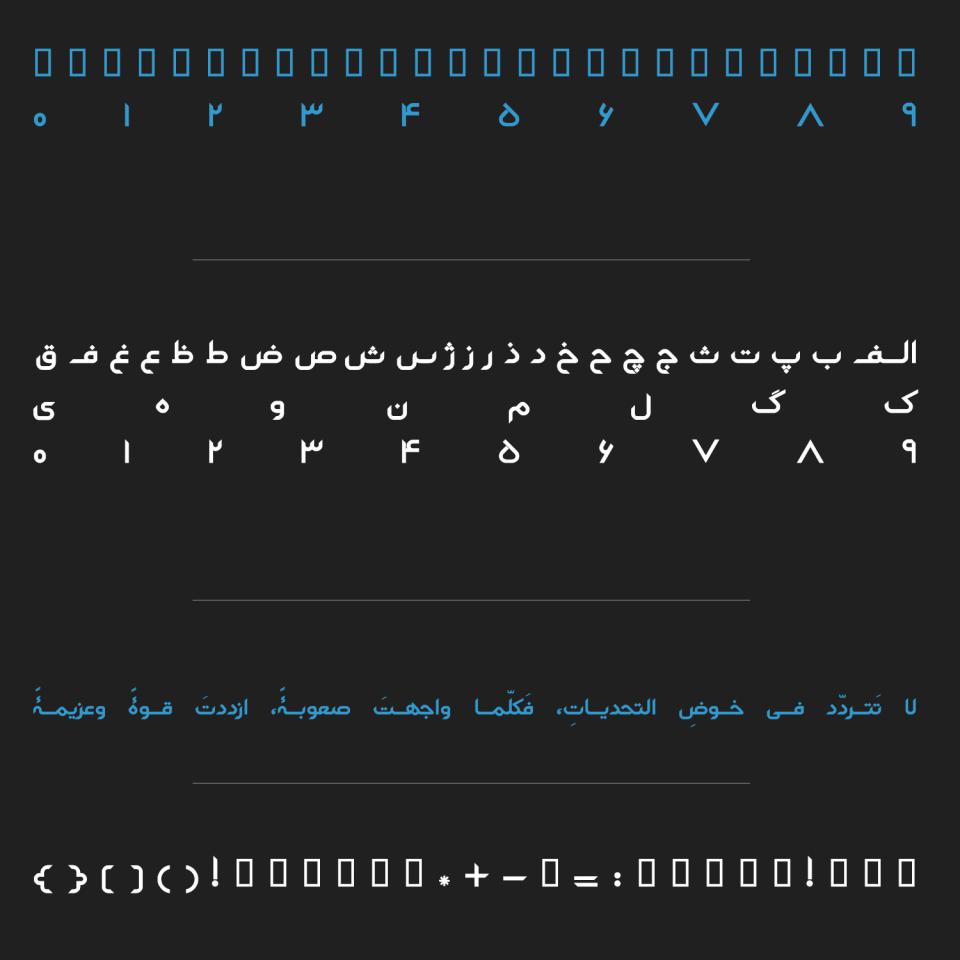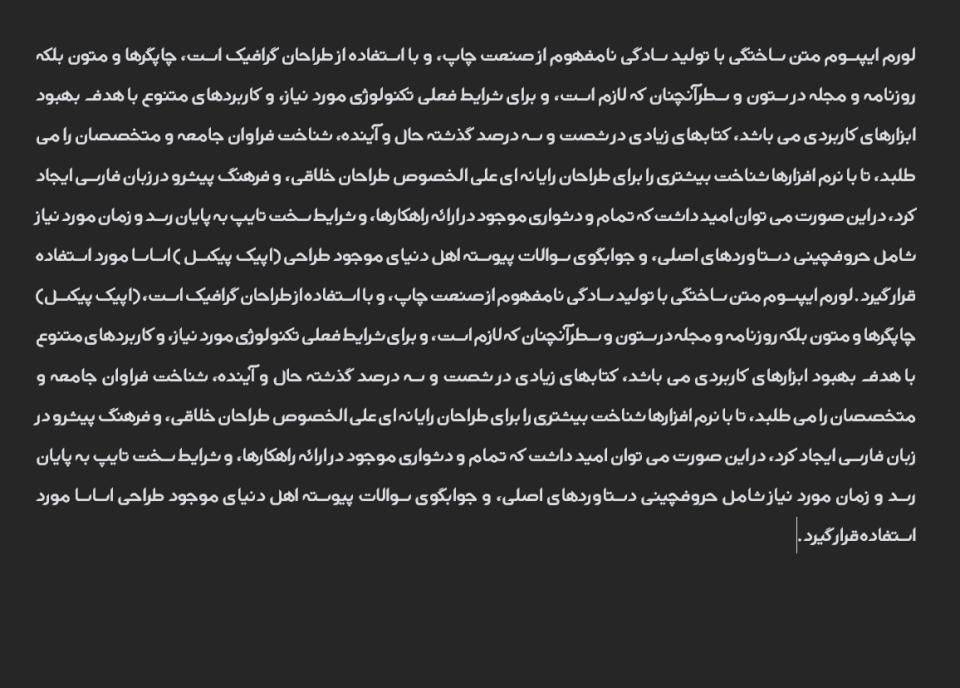
5 فونت آسمان فارسی
یکی از ویژگی های برجسته فونت آسمان، طراحی منحصربه فرد حروف آن است که هم در متن های طولانی و هم در عناوین کوتاه، خوانایی بالایی را ارائه می دهد. این ویژگی، آسمان را به گزینه ای مناسب برای طراحی لوگو، پوستر، وب سایت و سایر پروژه های گرافیکی تبدیل کرده است. علاوه بر این، فونت آسمان به صورت رایگان در دسترس است و شما می توانید بدون هیچ هزینه ای از آن در پروژه های شخصی و تجاری خود استفاده کنید.
با وجود مزایای فراوان، لازم به ذکر است که فونت آسمان تنها شامل حروف فارسی و اعداد است و از زبان های دیگر پشتیبانی نمی کند. همچنین، این فونت تنها در دو حالت معمولی (Normal) و ایتالیک (Italic) ارائه می شود و فاقد وزن های دیگر مانند ضخیم (Bold) یا خیلی ضخیم (Black) است. با این حال، با توجه به طراحی زیبا، خوانایی بالا و رایگان بودن، فونت آسمان همچنان یک انتخاب عالی برای طراحان و کاربران فارسی زبان به شمار می رود.